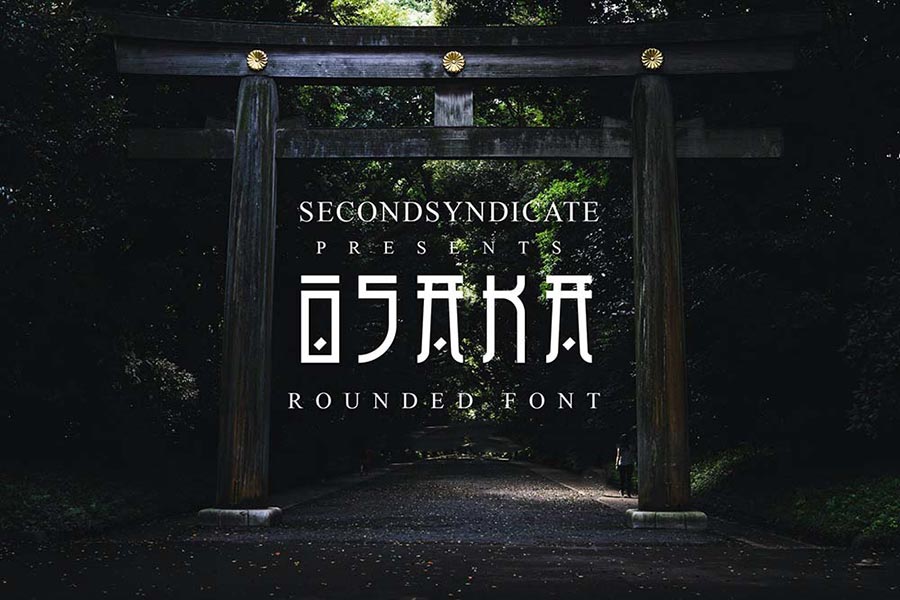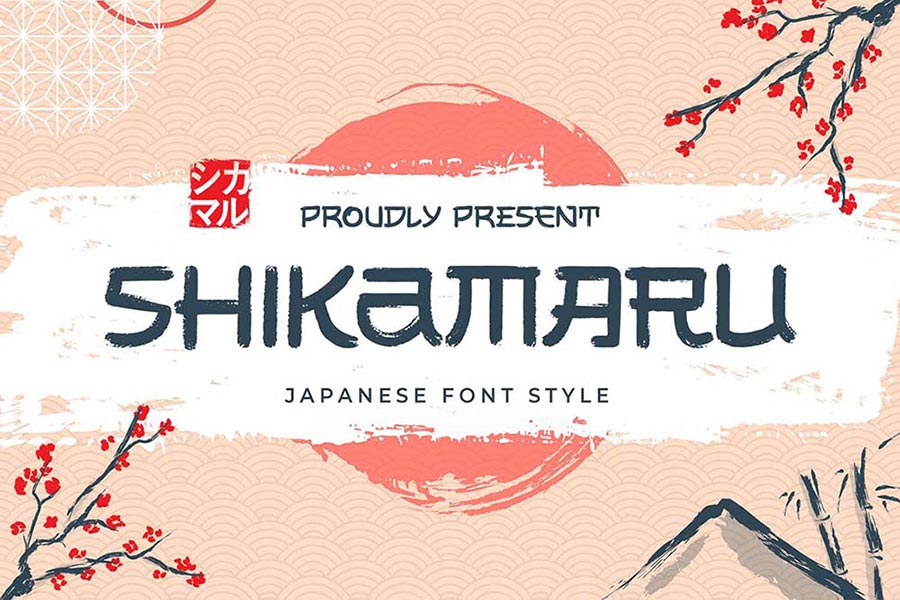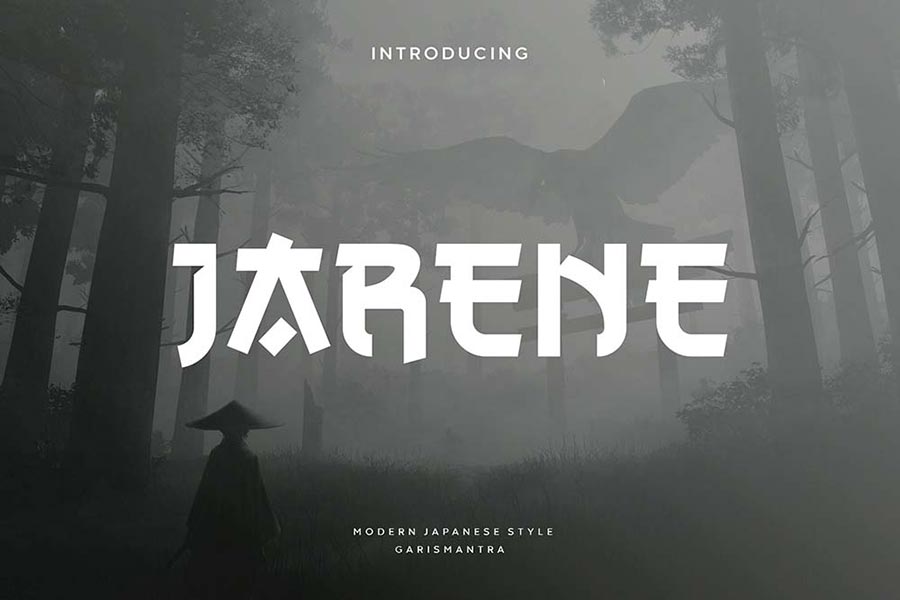
Chia Sẻ Miễn Phí Font Chữ Kiểu Nhật Dành Cho Các Design Tuyệt Đẹp
Trong lĩnh vực thiết kế đồ họa, việc lựa chọn font chữ phù hợp đóng vai trò vô cùng quan trọng, không chỉ góp phần truyền tải thông điệp mà còn tạo nên phong cách và dấu ấn riêng cho sản phẩm. Đặc biệt, các font chữ kiểu Nhật đang ngày càng được ưa chuộng nhờ vào sự độc đáo và tinh tế mà chúng mang lại.
Font Chữ Kiểu Nhật – Sự Tinh Tế Trong Thiết Kế
Font chữ kiểu Nhật thường được biết đến với những đường nét mềm mại, thanh thoát nhưng không kém phần mạnh mẽ. Chúng thường được sử dụng trong các thiết kế mang phong cách tối giản, hiện đại nhưng vẫn giữ được nét truyền thống. Đây là lựa chọn hoàn hảo cho các dự án thiết kế cần sự mới mẻ và khác biệt.
Lợi Ích Khi Sử Dụng Font Chữ Kiểu Nhật
1. Tạo Điểm Nhấn Độc Đáo: Font chữ kiểu Nhật giúp tạo ra điểm nhấn đặc biệt cho thiết kế của bạn, dễ dàng thu hút ánh nhìn của người xem.
2. Đa Dạng Phong Cách: Với sự đa dạng về kiểu dáng và phong cách, bạn có thể dễ dàng tìm thấy một font chữ kiểu Nhật phù hợp với bất kỳ dự án nào, từ thiết kế logo, poster đến các ấn phẩm truyền thông.
Việc sử dụng font chữ kiểu Nhật không chỉ giúp nâng cao giá trị thẩm mỹ của sản phẩm thiết kế mà còn thể hiện sự sáng tạo và chuyên nghiệp của nhà thiết kế. Với các nguồn tài nguyên miễn phí hiện có, việc tích hợp các font chữ này vào dự án của bạn chưa bao giờ dễ dàng hơn. Hãy khám phá và tận dụng những lợi ích mà font chữ kiểu Nhật mang lại để tạo nên những tác phẩm thiết kế ấn tượng và khác biệt.